Si pensamos en el lettering de los rótulos y pósters de las películas de terror antiguas, seguramente nos estemos refiriendo a este Alfabeto Lettering de Terror que ya vimos en un artículo anterior, inspirado en películas como «El Gabinete del Doctor Caligari». Sin embargo, hoy vamos a fijarnos en el lettering de terror efecto sangre o derretido y este lo solemos ver más en películas de terror de los años 70 y años 80, con ese tipo de letra que parece estar derramando sangre o estar derritiéndose, como si fuese un monstruo viscoso deshaciéndose. Primero, vamos a ver algunos carteles de películas de terror de esa época, después vamos a ver un alfabeto de ejemplo y finalizaremos con algunos ejemplos de hand lettering de terror sangriento.
CARTELES DE PELÍCULAS CON LETTERING DE TERROR EFECTO SANGRE
Veamos algunos carteles y rótulos de películas de terror con lettering de terror efecto sangre de los años 70 y 80 que trajeron este estilo de letra sanguinolenta que luego tanto se iba a llevar.
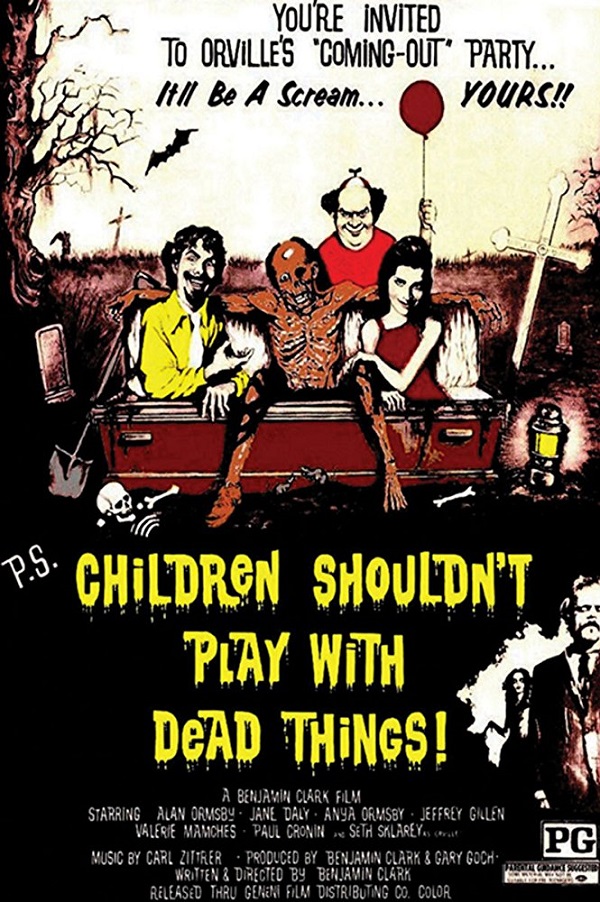
Quizás el lettering de terror efecto sangre más conocido es el del cartel de la película «La noche de los muertos» del año 1972, o también llamada «Children shouldn’t play with dead things», es decir, «Los niños no deberían jugar con cosas muertas».
¡Fijaos en este rótulo animado de la película porque aún da más miedo!
Aquí tenemos otro cartel, en este caso de la película de terror «The Stuff», del año 1985, en cuyo poster también se utilizó este tipo de lettering de terror pero, en vez de sangre, da más bien el efecto derretido, con trazos más gruesos. Esto es porque la película va de una sustancia espesa y lechosa que brota del suelo, así que este tipo de letra da más bien esta sensación, que en inglés se llama melting.
Una versión algo más actualizada del lettering de terror efecto sangre es la del cartel de la película «Slither», del año 2006. Esta película va sobre un parásito que invade el cuerpo de una persona, así que el lettering es la perfecta combinación entre algo sangriento y una criatura viscosa que se mete en las entrañas.
ALFABETO LETTERING DE TERROR SANGRE
Ahora que ya conocemos un poco el origen del lettering de terror efecto sangre y su aplicación en rótulos y carteles de películas, os traemos un alfabeto que os puede servir de ejemplo a la hora de dibujar vuestros propios letterings de terror sangrientos.
EJEMPLOS HAND LETTERING DE TERROR SANGRE
Ahora, si queréis dibujar este tipo de letras de terror sangrientas o hacer vuestros propios hand letterings para Halloween o para invitar a vuestros amigos a una sesión de películas de terror en vuestra casa, podéis hacerlo.
Este lo hemos hecho nosotros siguiendo el alfabeto que os hemos propuesto.
También os traemos este otro ejemplo de lettering sangriento dibujado a mano de Shoo Rayner y que incluso en su canal de Youtube os enseña cómo hacerlo.